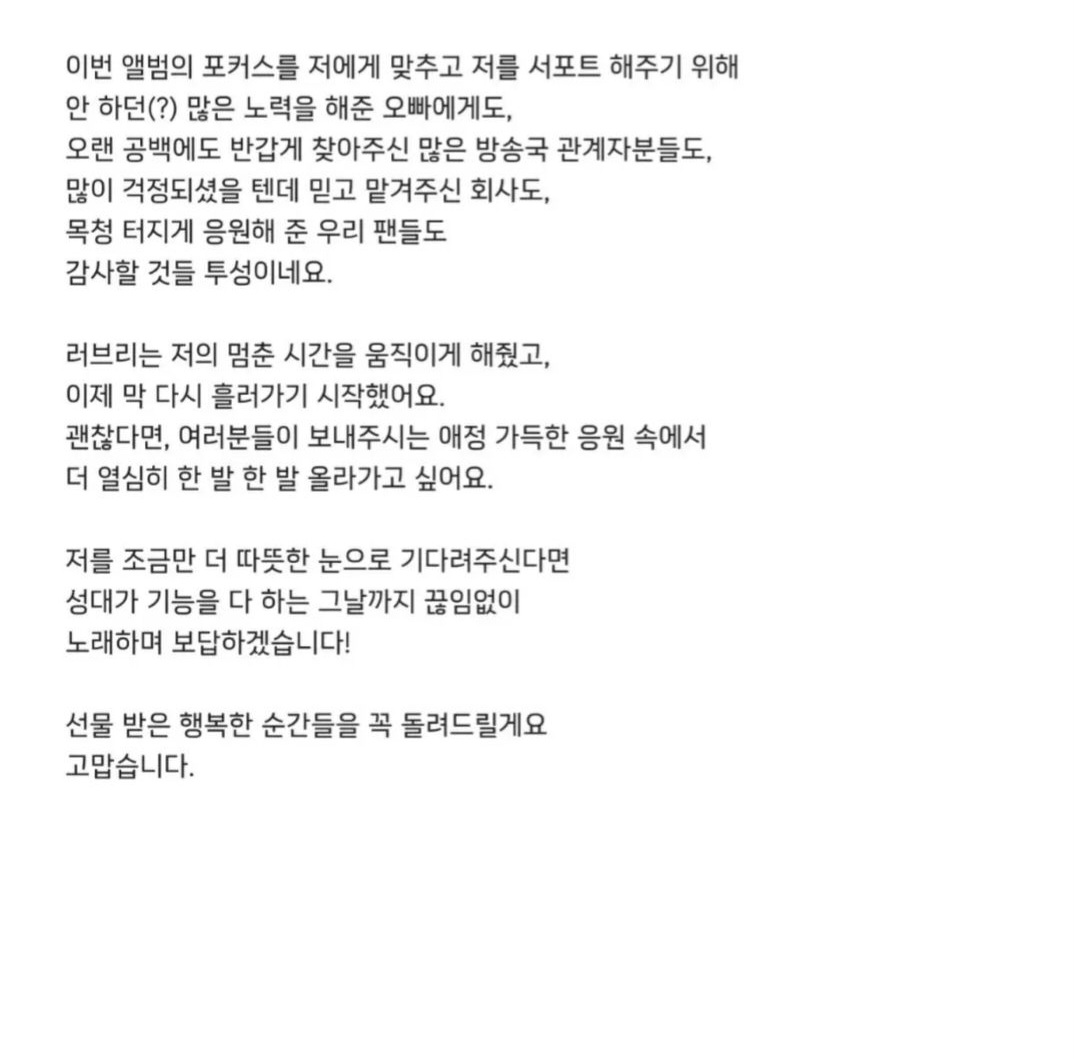
폰트 궁금해요 als*** 2024.04.05 폰트가 깔끔해서 사용하고 싶은데 알려주시면 감사하겠습니다. 댓글 0 등록 sta*** Aa합정산스 같네요 https://blog.naver.com/aafont/221489420600 2024-04-05 답글 달기 댓글 더보기 쉽고 빠르게 가장 비슷한 폰트를 알고 싶다면? 이미지로 검색하기
Aa합정산스 같네요 https://blog.naver.com/aafont/221489420600